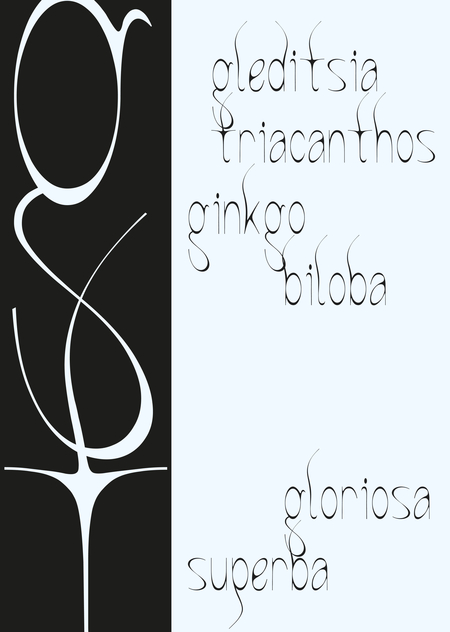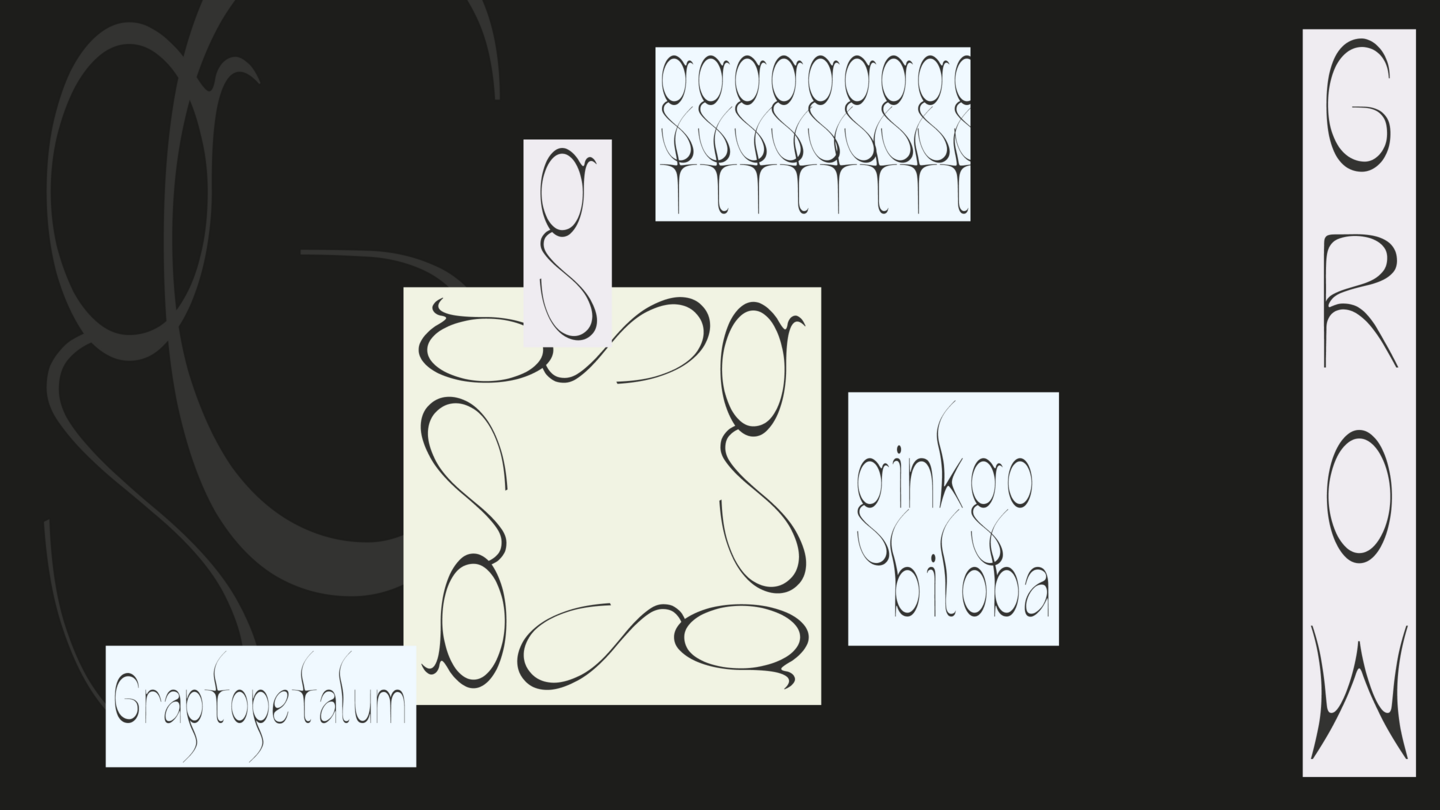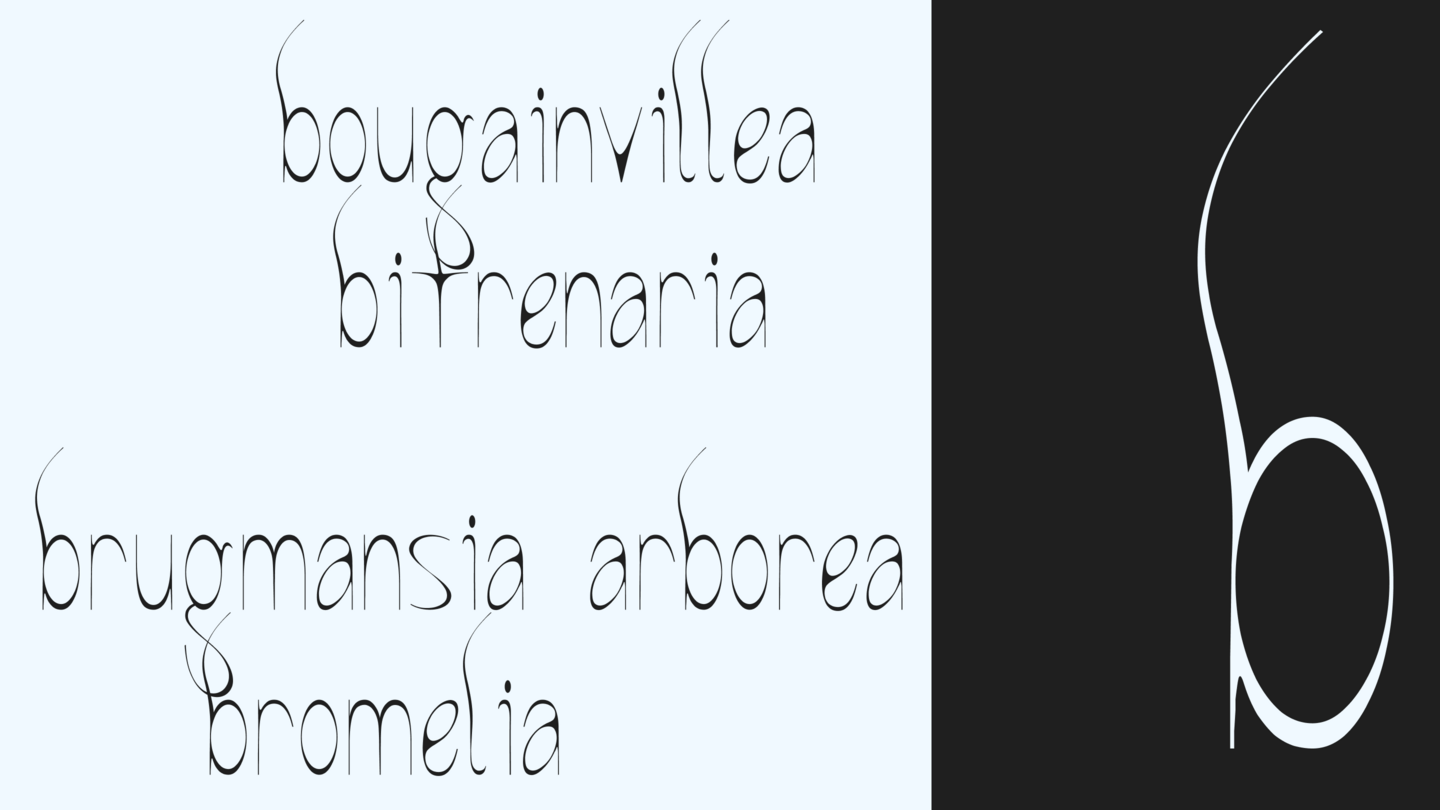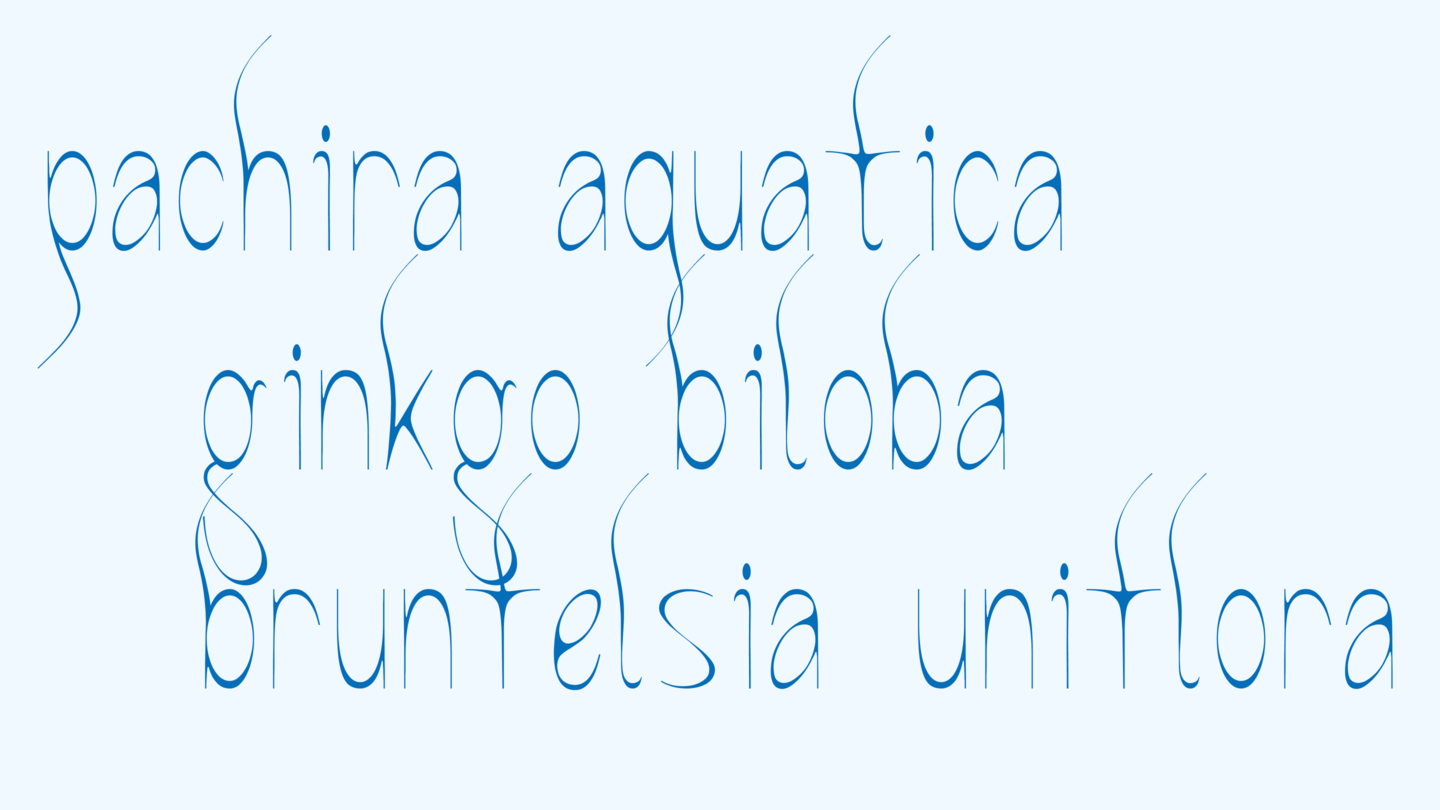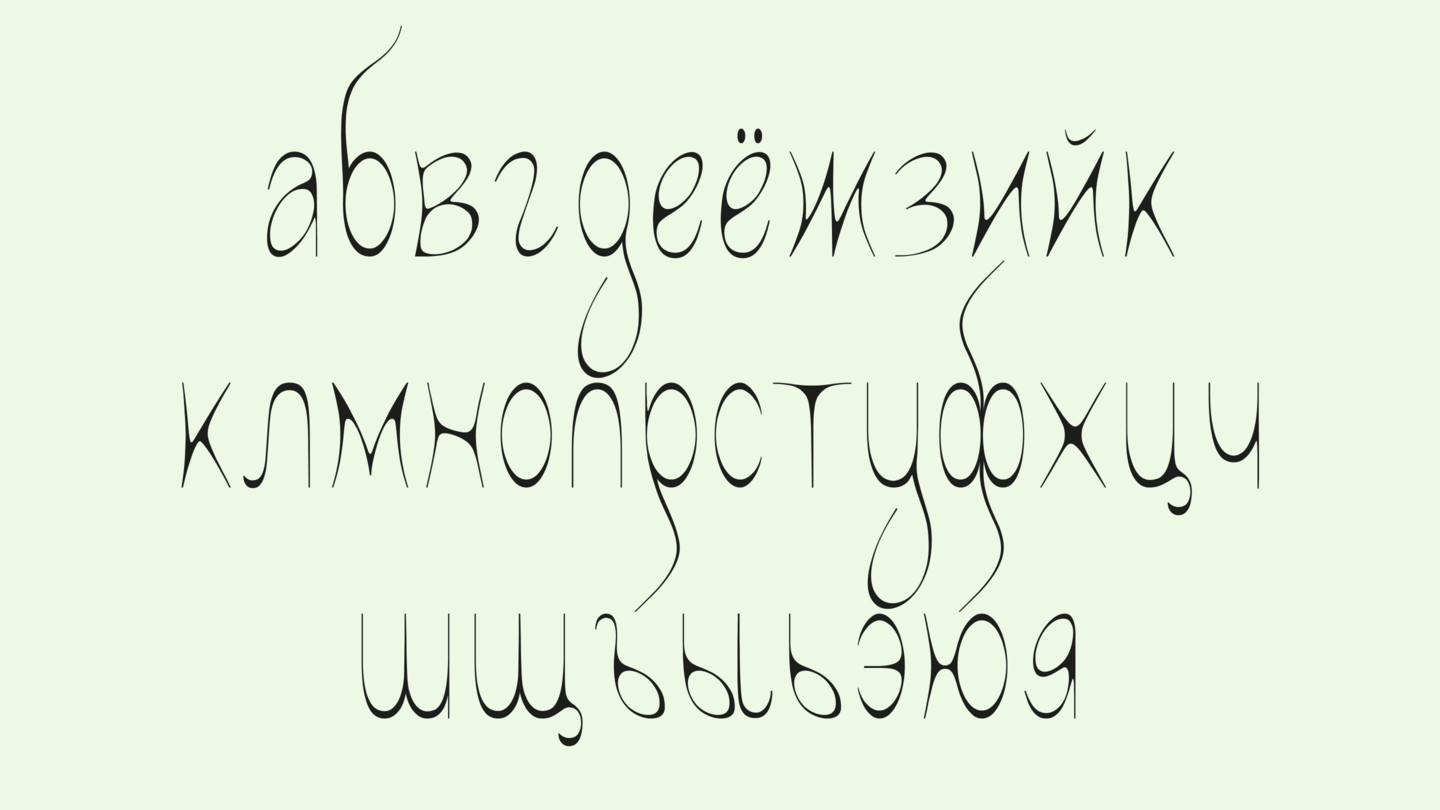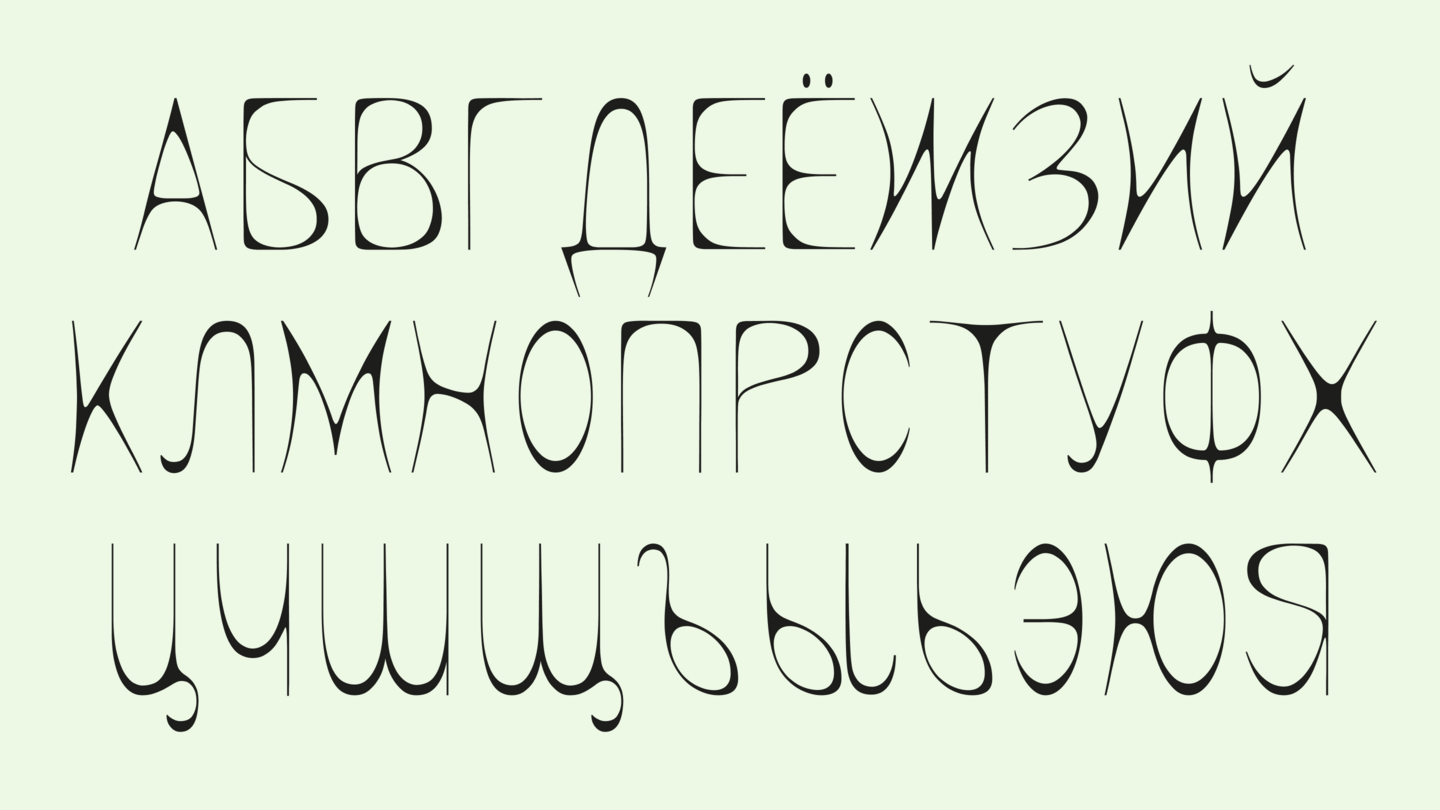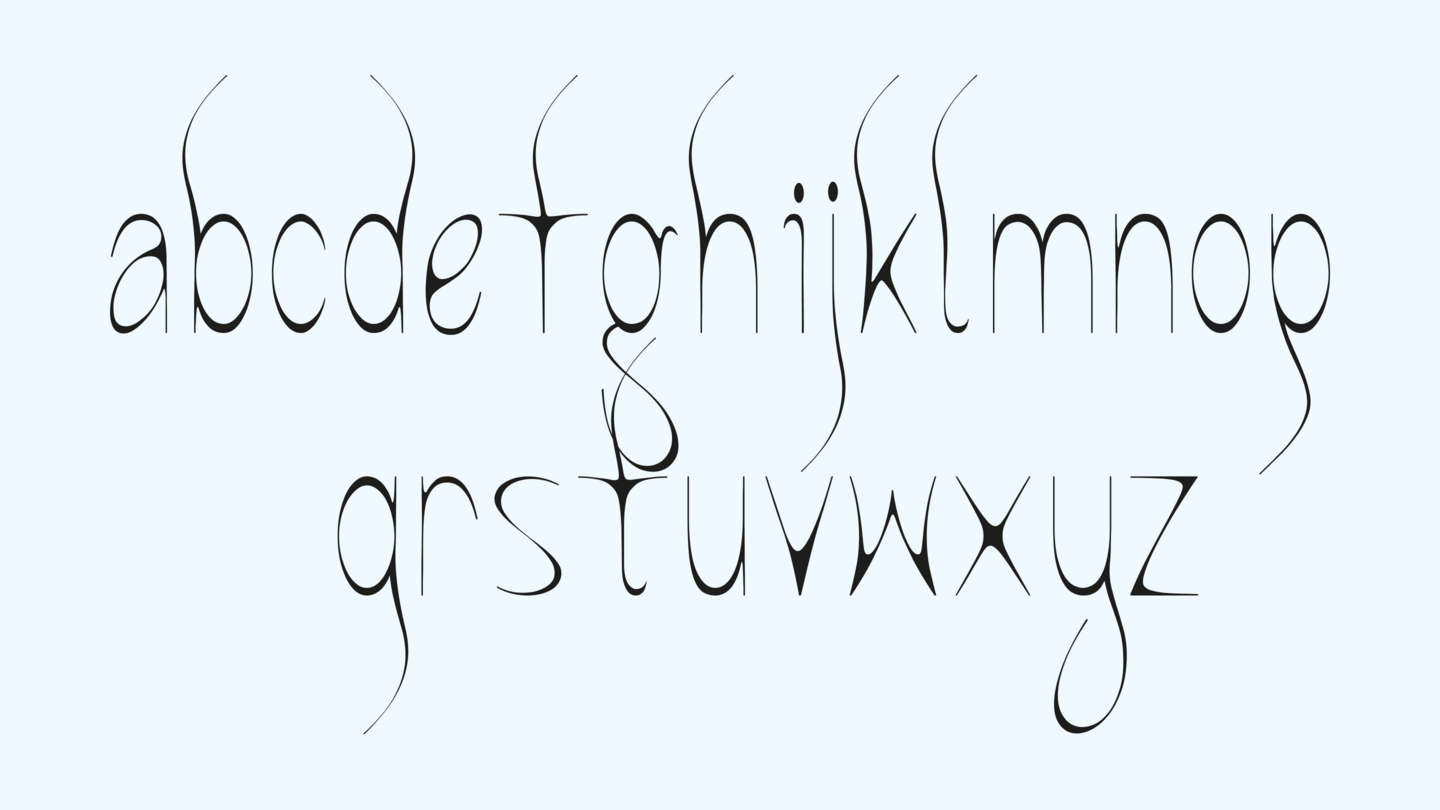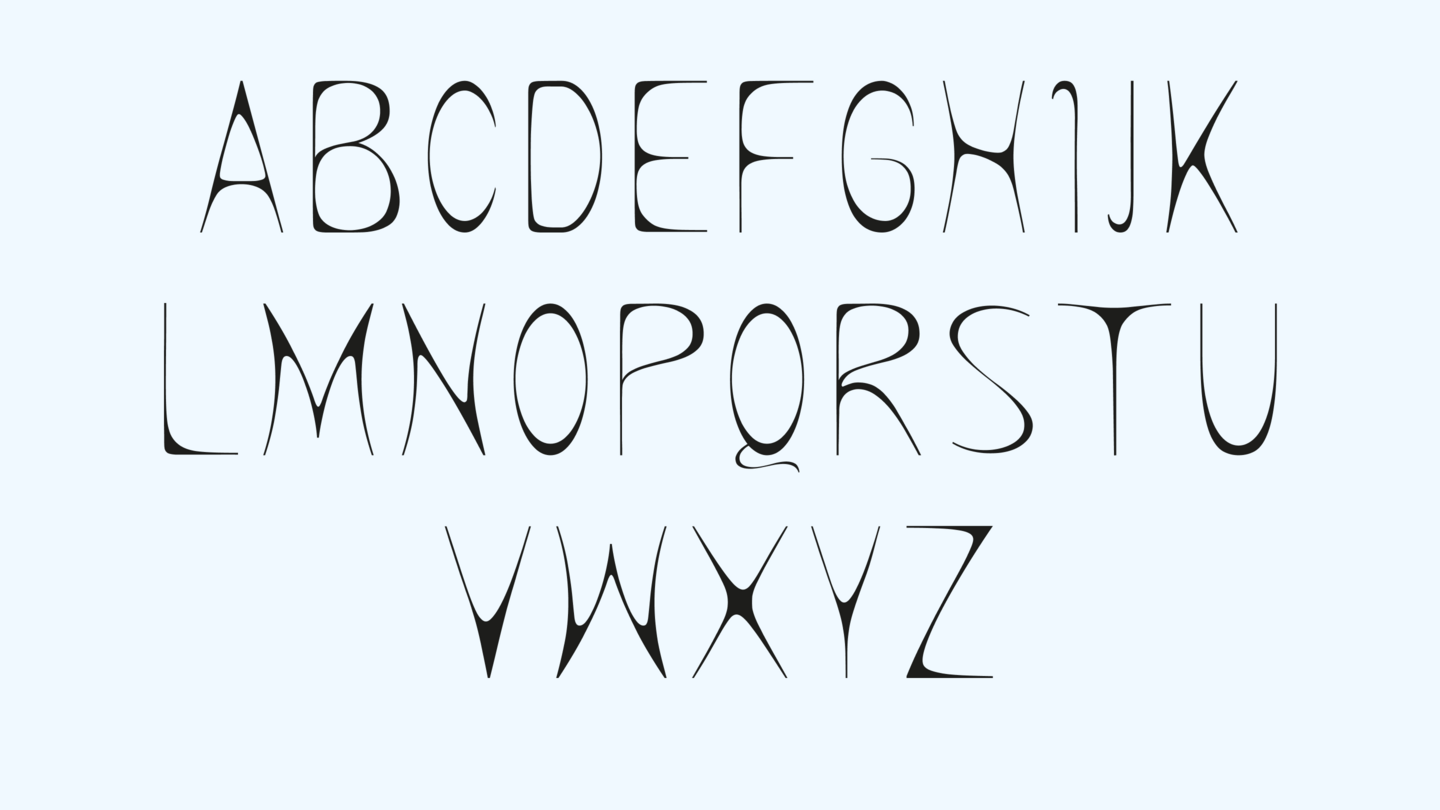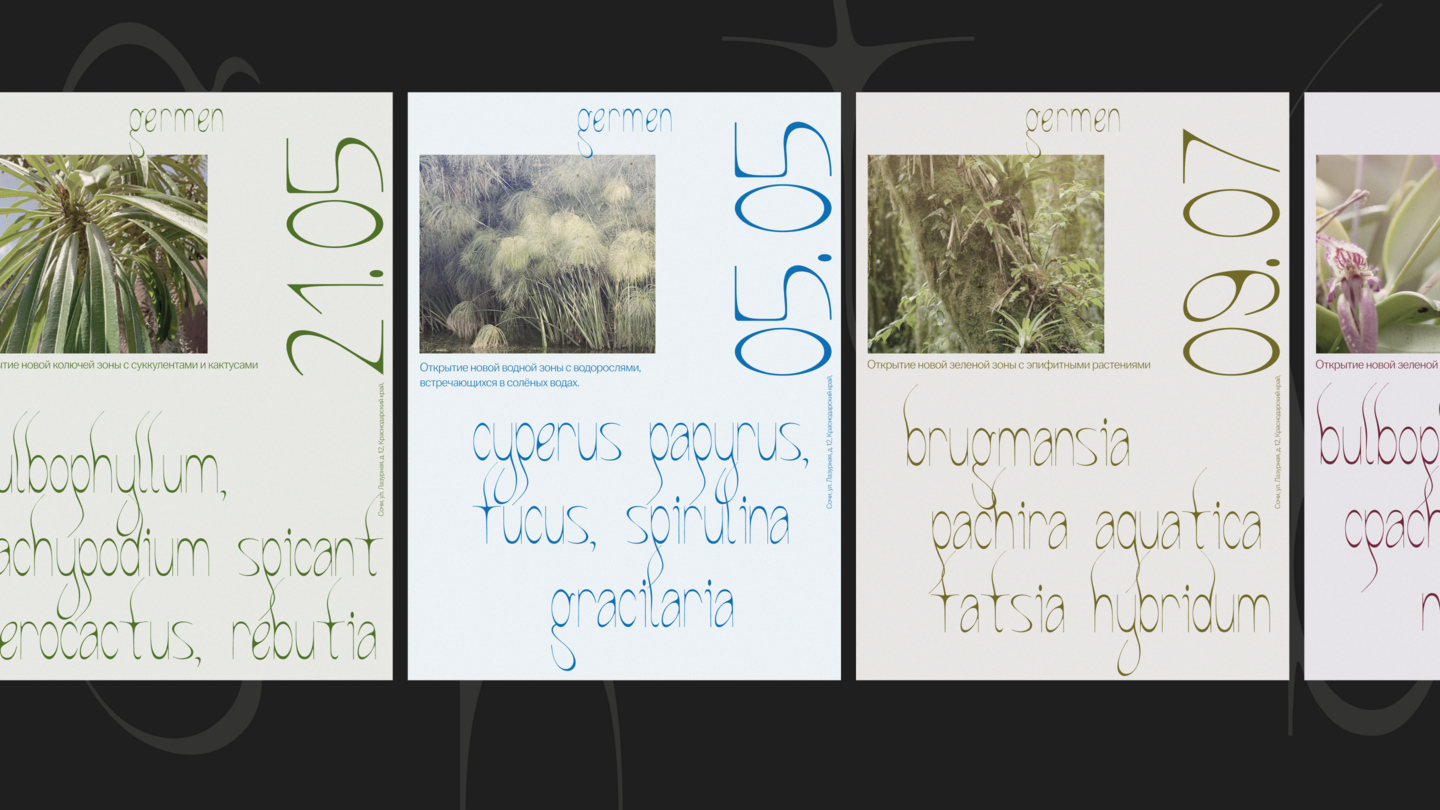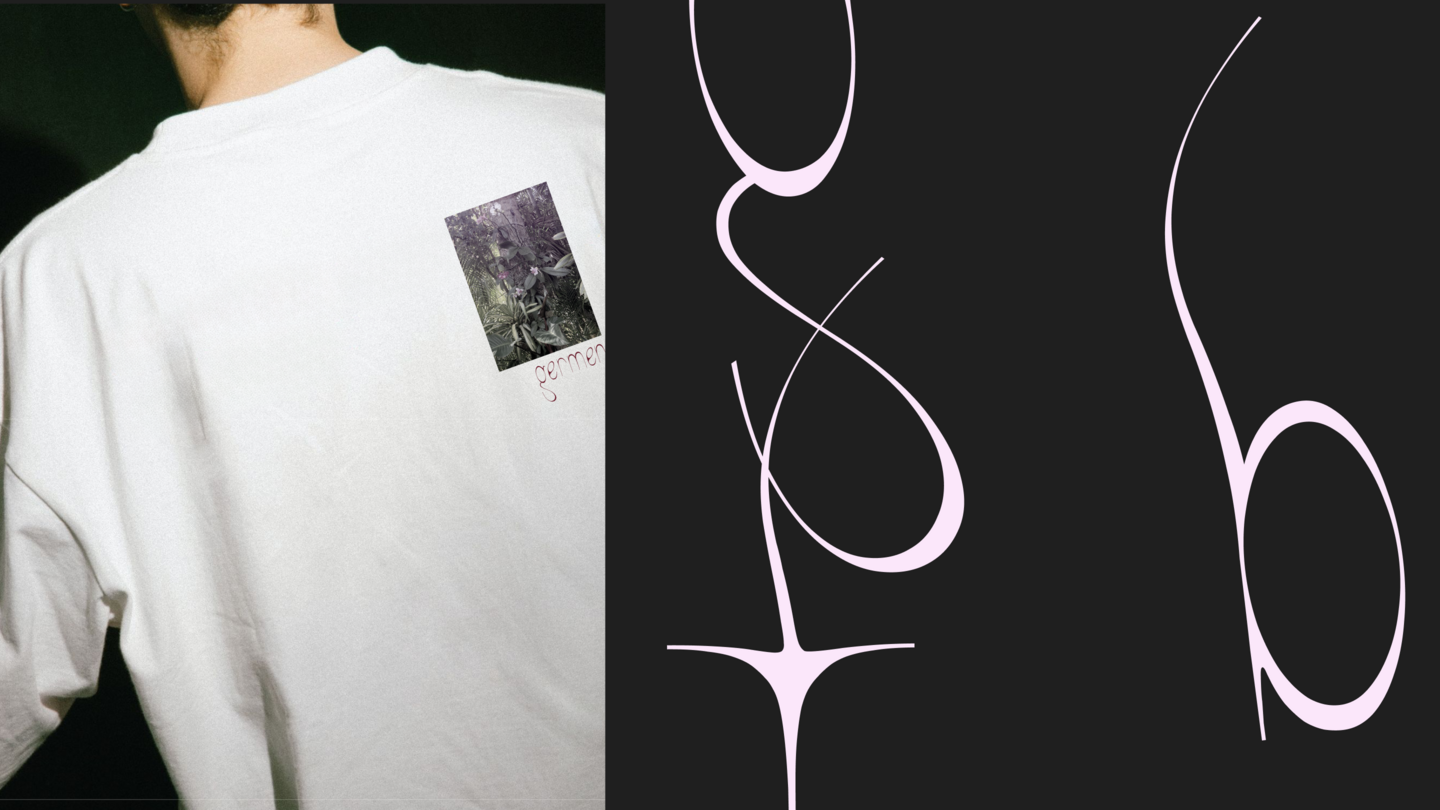
Germen Font
Germen Font — это акцидентный шрифт с обратным контрастом: массивные опорные штрихи сочетаются с очень тонкими линиями, из-за чего буквы выглядят хрупкими, плавными и острыми одновременно.
Он вытянутый и вертикальный, с высоким силуэтом и длинными выносными элементами.